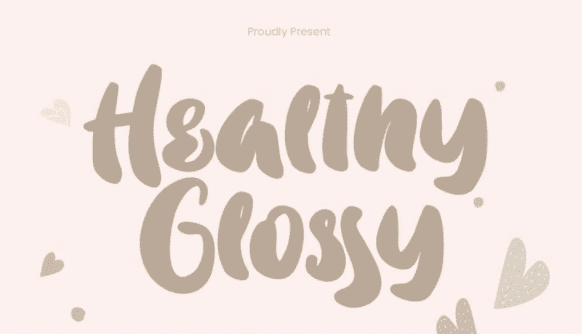
Название: Healthy Glossy Font (2021)
Здоровый глянцевый рукописный шрифт. Идеально подходит для всех ваших ремесленных проектов. Этот шрифт идеально подходит для карфта, декора фермерского дома, веб-сайтов, svg-дизайнов, домашнего декора, брендинга, блогов, логотипов, приглашений и многого другого.
Прописные и строчные буквы
Цифры и пунктуация
Многоязычный
Лигатуры
Кодировка PUA